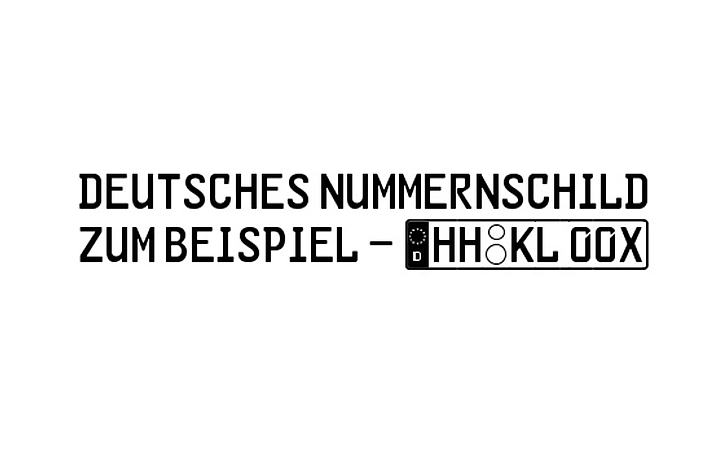
GL-Nummernschild-Mtl (ドイツのナンバープレート)は、ドイツで車のナンバープレートに使われているフォントです。書体デザイナーKarlgeorg Hoeferによって作成され、ドイツ自動車車両法で規定されています。この書体はFE-Schriftと呼ばれ、文字や数字が変造できないように作成されています。例えば、「1(イチ)」を「I(アイ)」に、「0(ゼロ)」を「O(オー)」に手を加えて書き換えようとしても、書き換えができないようになっています。
書体の幅が狭い「GL-Nummernschild-Eng」もあります。